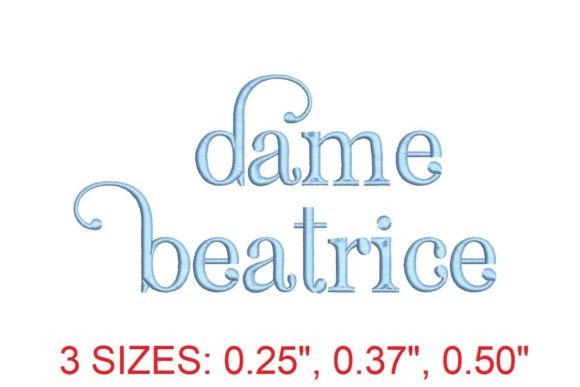
Dame Beatrice Embroidery Font
Việc tìm kiếm các thành phần thiết kế phù hợp có thể là một thách thức, nhưng Dame Beatrice Embroidery Font cung cấp một bộ sưu tập đặc biệt giúp nâng tầm công việc của bạn ngay lập tức.
Build Quality & Specifications
Được chế tác với độ chính xác cao, Dame Beatrice Embroidery Font cung cấp các vector sạch, kiểu chữ mượt mà và giấy phép thương mại để bạn yên tâm.
Who Is This Best For?
Cho dù bạn đang tạo sản phẩm POD (In theo yêu cầu), thiệp mời đám cưới hay đồ họa mạng xã hội, Dame Beatrice Embroidery Font đều là một sự lựa chọn lý tưởng.
Mẹo chuyên gia: Kết hợp các yếu tố này với các phông chữ bổ sung để tạo ra các thiết kế độc đáo, bắt mắt nổi bật trên thị trường.